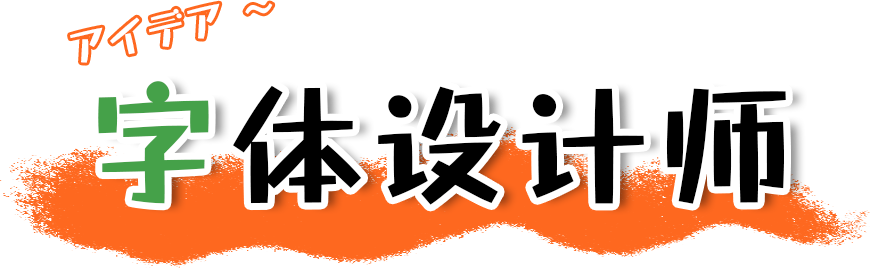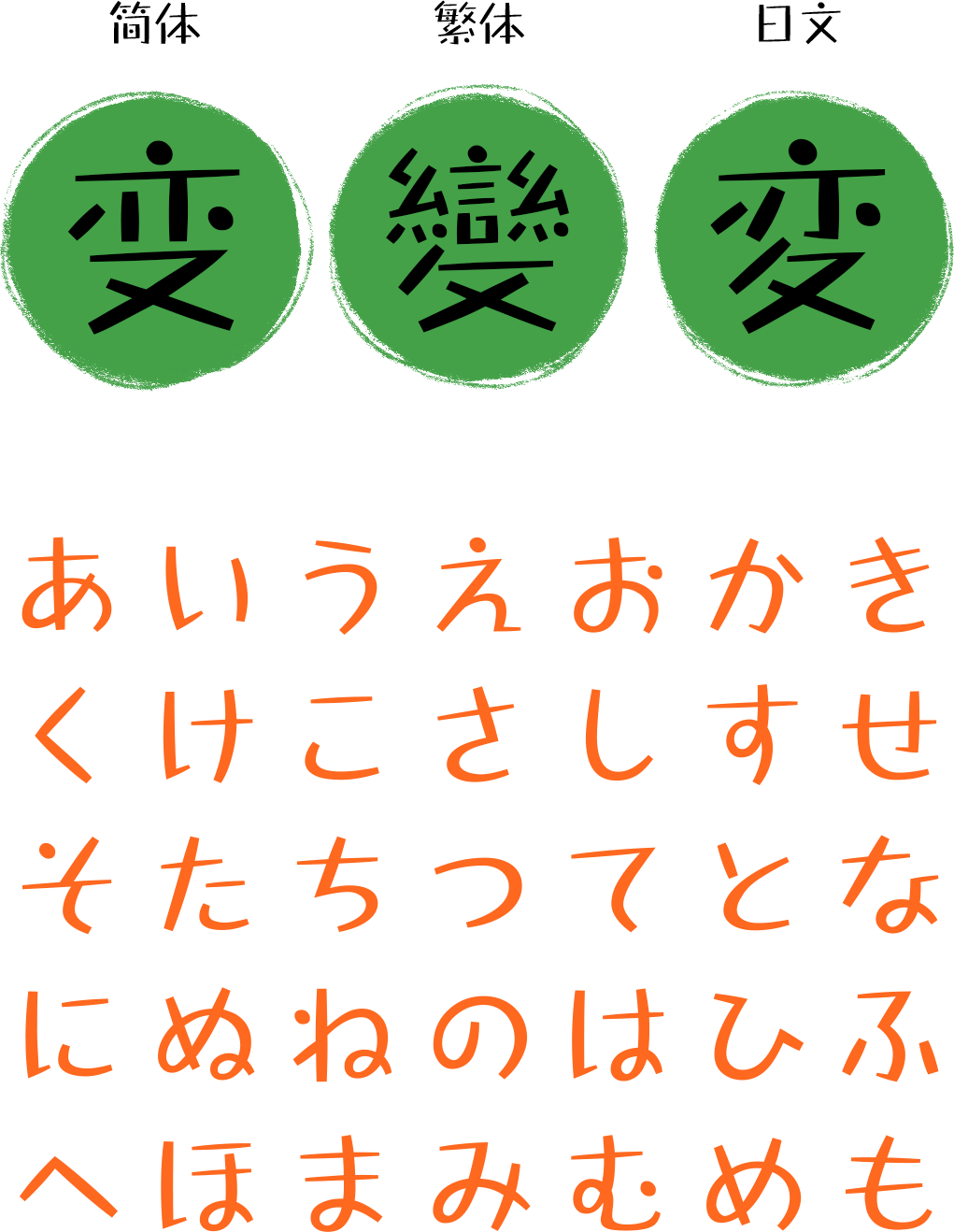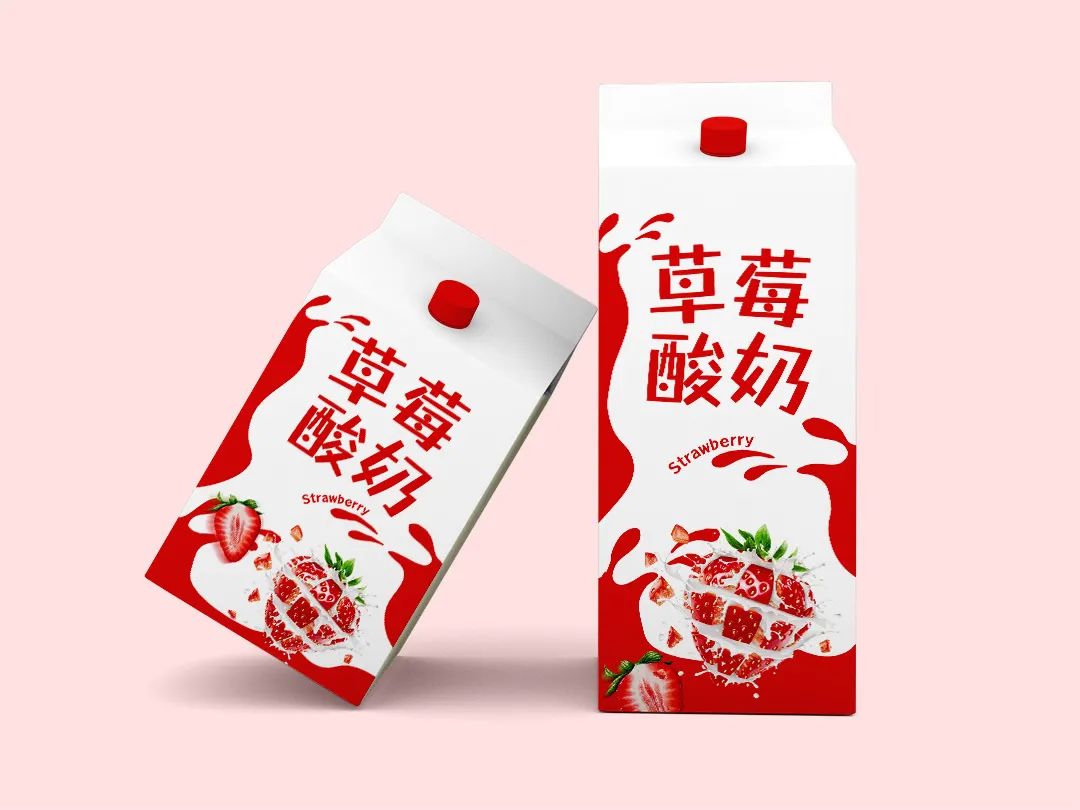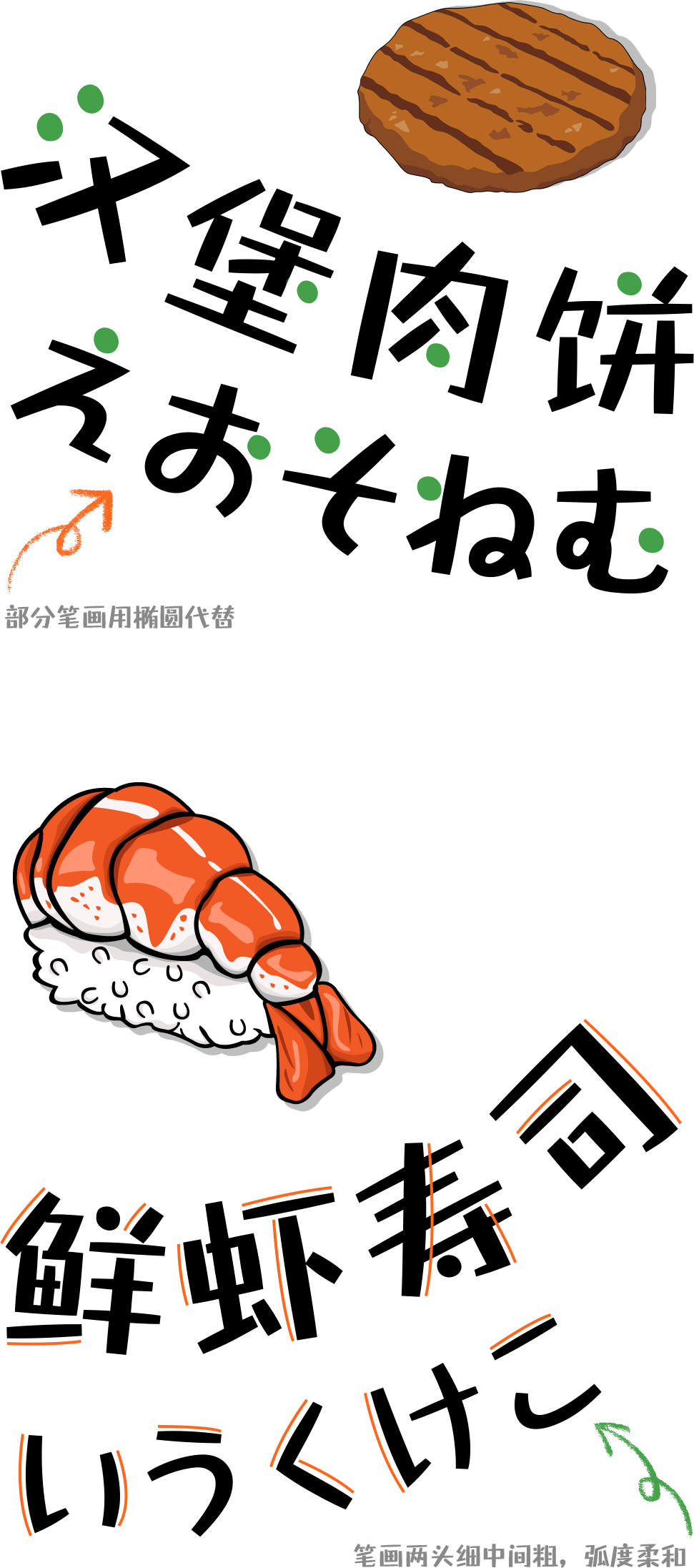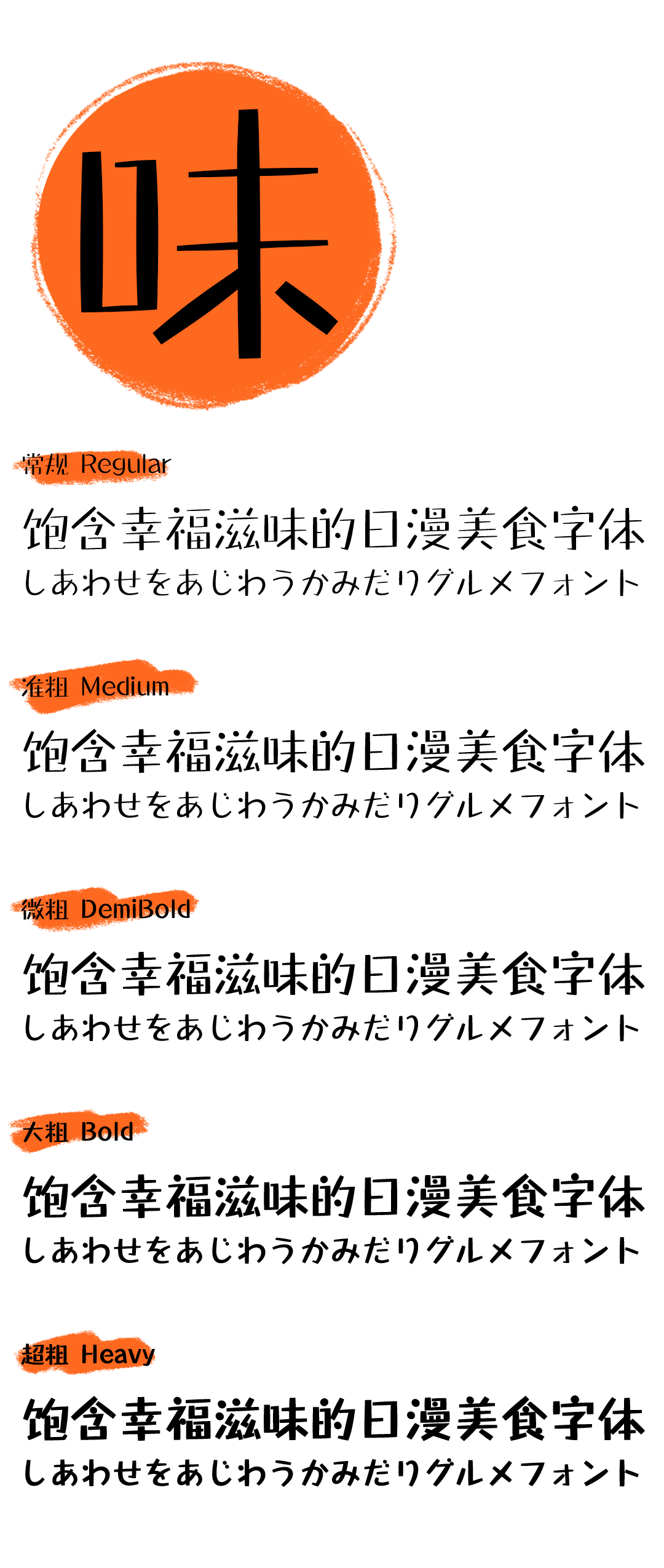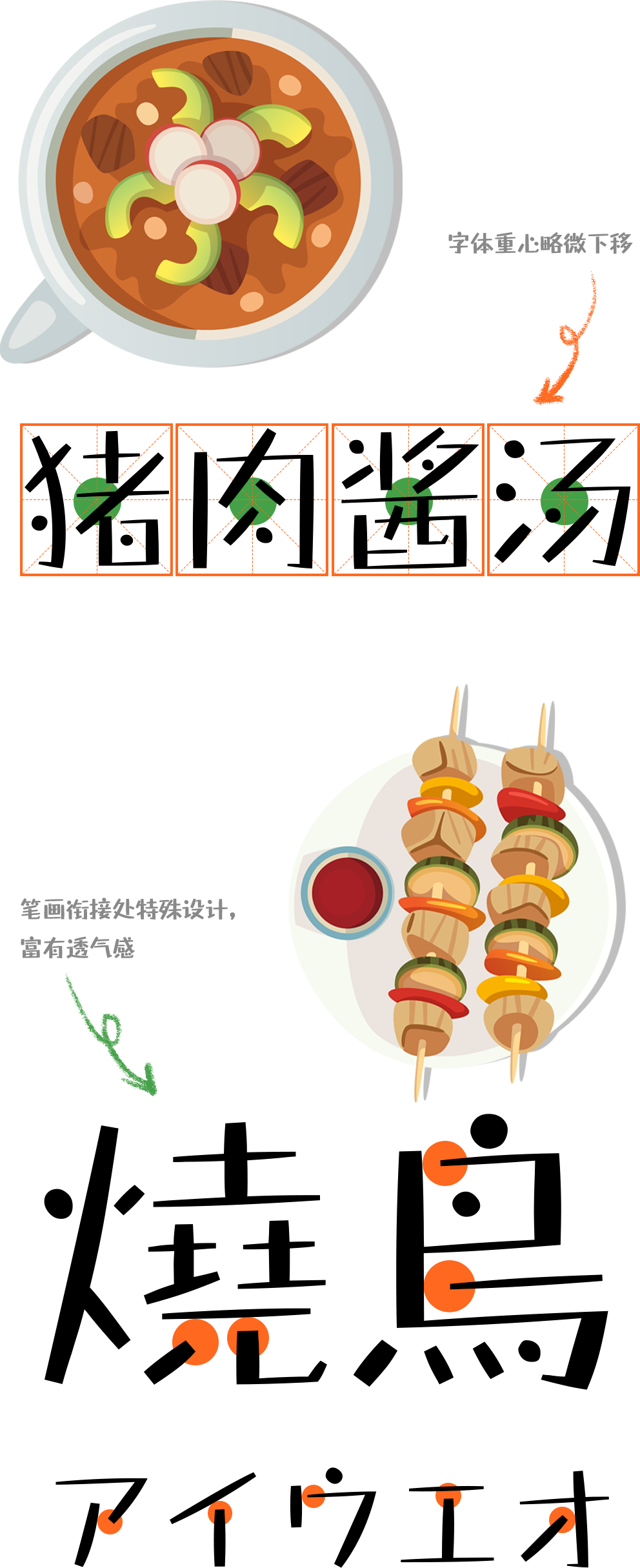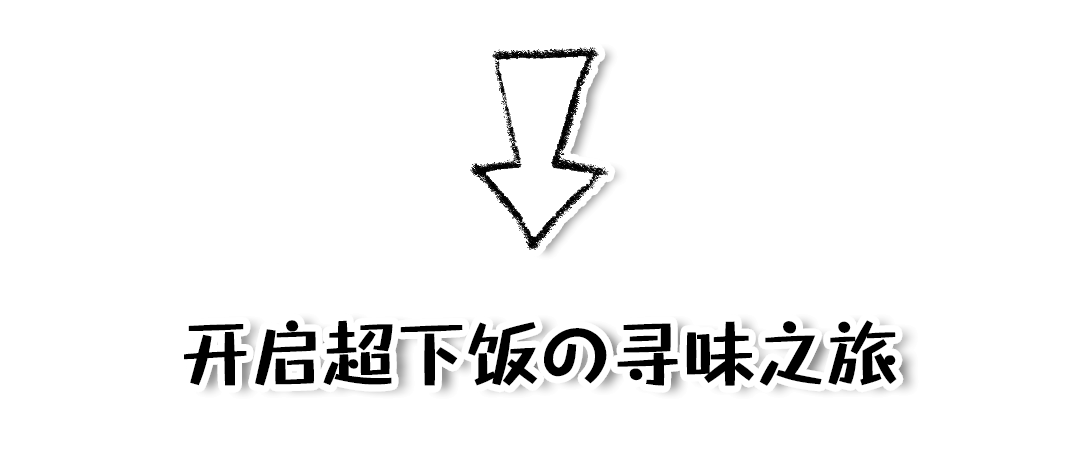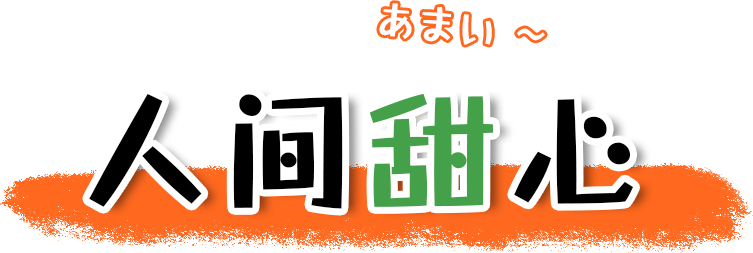
日系美食漫画创意字体——可爱有趣的GEETYPE高原颜漫体!字体资讯
人生是苦的,只有吃的时候才会甜进心里。美食是幸福的证据,温暖治愈的日漫美食番,热乎乎香喷喷的食物,陪伴我们度过每一个孤独的夜晚。
今日饭点没有胃口❓日本著名字体匠人高原新一化身日漫美食家,给大家准备了超美味的精神粮食,那就是日系美食漫画创意字体——可爱有趣的中日双语字体【GEETYP高原颜漫体】。
GEETYPE高原颜漫体是一款以手写感为设计基础的直线字体,弧度饱满的笔画,柔和简约的直线字形,轻盈卡通的手写感,仿佛置身舒缓治愈的漫画中。
简化部分笔画,将字体重心下移,松散的中宫结构,舒展的留白空间,笔画衔接处适度拆分,使字体明朗可爱,富有透气感。
笔画两头略细中间略粗并加入柔和的弧度,横竖和撇捺的粗细比例为2:1,整体粗细平衡。部分点横用随机适配的椭圆元素代替,视觉效果呈现趣味性、卡通感。
提供中日双语简繁日字形,可体验多元的应用。设置了常规、准粗、微粗、大粗、超粗5款字重,且支持可变字体,可随心调节字体粗细,匹配设计应用的不同排版需求。
GEETYPE高原颜漫体可爱日漫的字体风格,与众不同的吸睛效果,能巧妙的提升视觉表现与阅读体验,激发多元设计灵感。
高原新一
日本最具怀旧風、人情味的字体设计大师。1949年1月出生于日本北海道上川郡江丹别(现・旭川市)。字体作品包揽多次石井赏金银奖/森泽字体大赛等多个大赛奖项, 海内外参展无数。
GEETYPE高原颜漫体|和书高原颜漫体
设计师:高原新一(日)